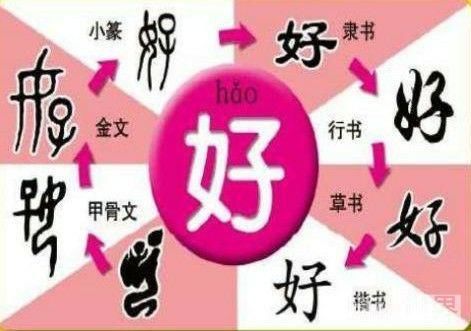
29. 中國文字在字體演變上,由甲骨文到楷書,試問秦始皇時,為彰顯功業,由大臣書寫的紀功碑在字體上由時代特徵判斷,會用那種字體?
(A)鐘鼎文
(B)篆文
(C)隸書
(D)楷書
(A)鐘鼎文 (金文,商朝中期)
(B)篆文 (秦)
(C)隸書 (始於秦,東漢達頂峰)
(D)楷書 (隸書變體)
甲骨文→金文→篆書→隸書→草書→楷書→行書
口訣:用假的金子賺你超開心
甲骨文→金文→篆書→隸書→楷書→草書→行書